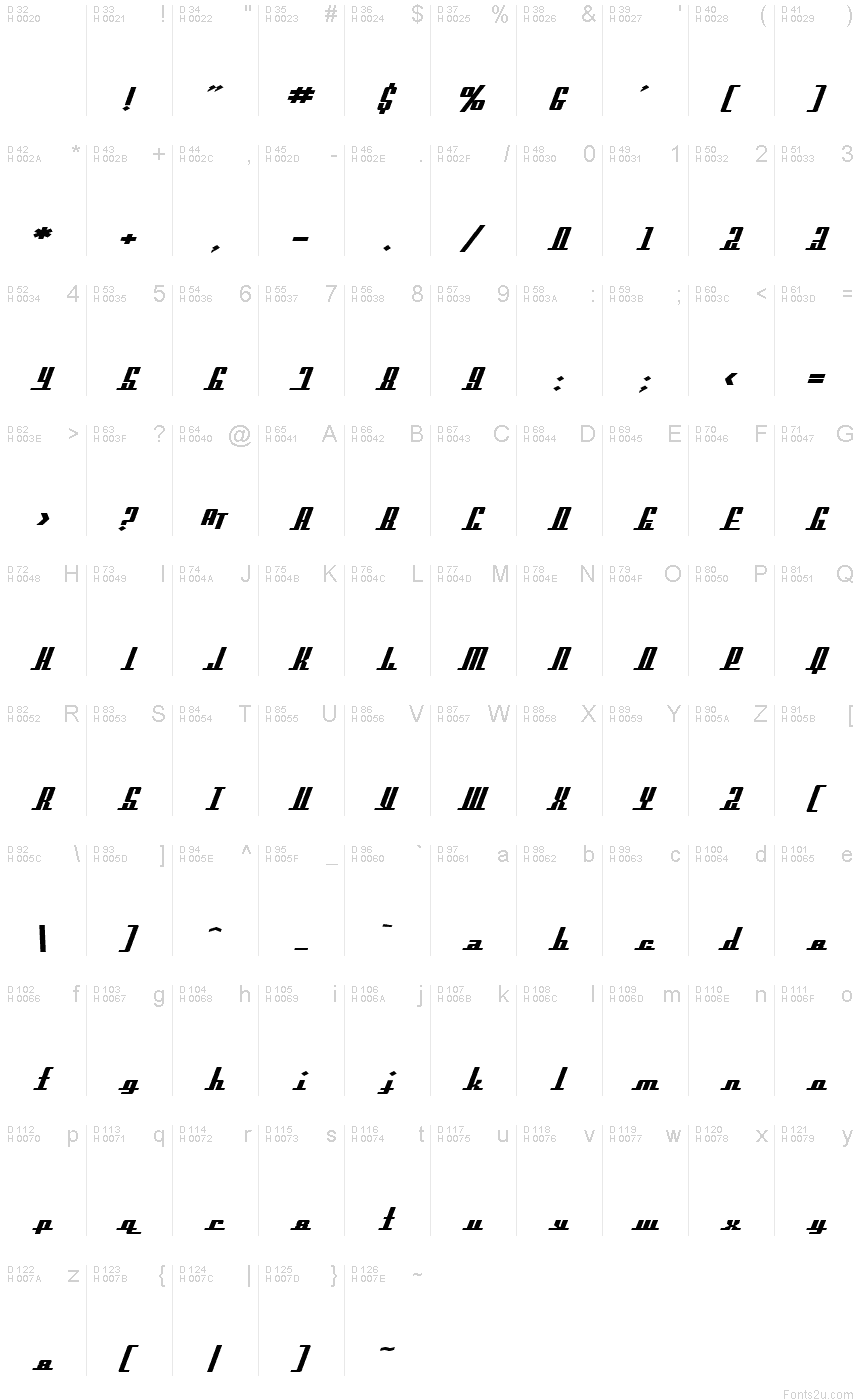
SF Americana Dreams Extended Bold od ShyFoundry to darmowy, utrzymany w stylu retro font display, który przywodzi na myśl dynamikę plakatów sprzed lat. Litery są grube, masywne i pochylone do przodu, a połączenie ostrych krawędzi z obłymi kształtami nadaje całości charakteru typowego dla amerykańskich szyldów z lat 70.
Krój ten naturalnie pasuje do brandingów w stylu „diner”, opakowań z duszą, okładek płyt, plakatów czy śmiałych nagłówków, gdzie jego szeroki, wyrazisty rytm gra główną rolę. Jako darmowy font świetnie sprawdzi się też w napisach tytułowych, szkicach logo czy krótkich grafikach na gadżety, dodając im nostalgicznego sznytu, bez popadania w westernowe banały.
SF Americana Dreams Extended
ShyFoundry
Derek Vogelpohl